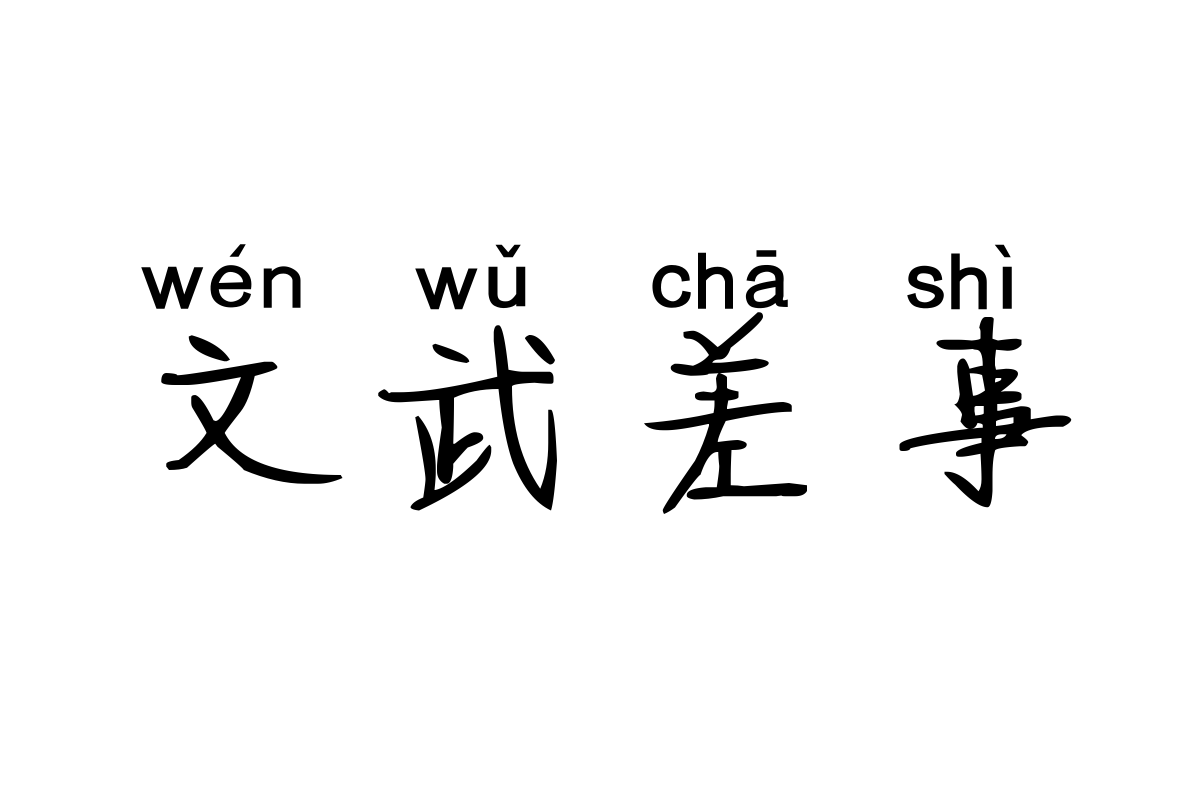
米开一米阳光拼音体是一款具有独特设计风格的中文字体。它的设计灵感来自于自然和阳光,旨在为用户提供一种舒适、愉悦的视觉体验。这款字体的特点包括:
1. 字形美观:米开一米阳光拼音体采用了简洁、流畅的笔画设计,使得整个字体看起来既优雅又大方。
2. 风格独特:该字体的设计灵感来源于自然和阳光,给人一种清新、明亮的感觉。这使得它在各种应用场景中都能展现出独特的魅力。
3. 适用范围广泛:无论是用于标题、正文还是广告宣传,米开一米阳光拼音体都可以轻松应对。它不仅适合印刷品,也适用于数字媒体,如网站、APP等。
总之,米开一米阳光拼音体是一款具有独特设计风格的中文字体,适用于各种应用场景。